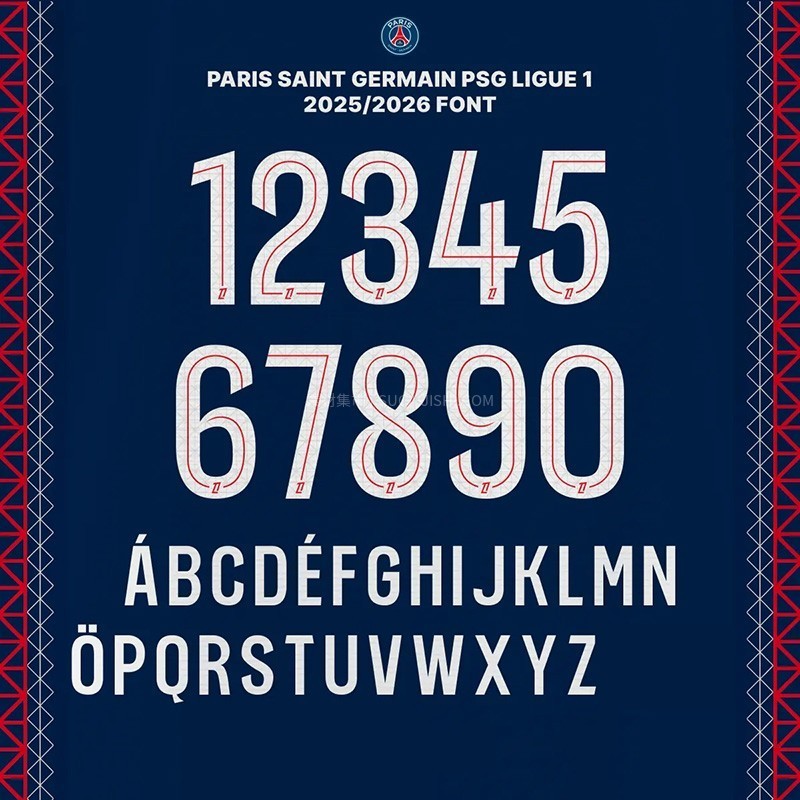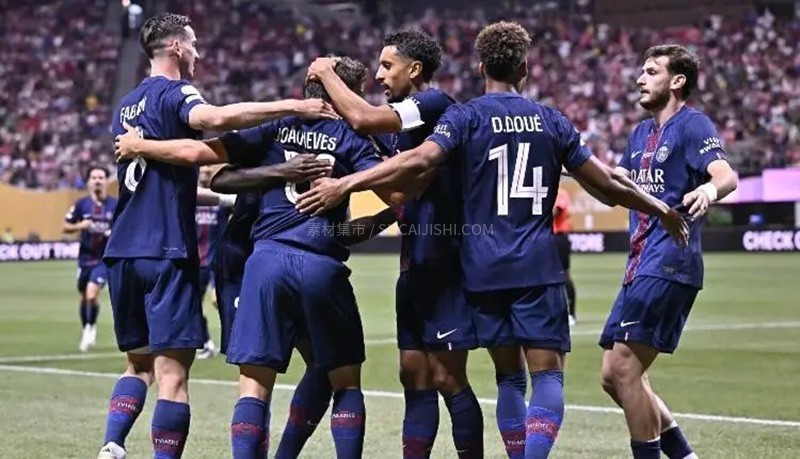
巴黎圣日耳曼为即将到来的法甲联赛 2025-26 赛季的球衣号码和队名字体,灵感源自球队的快速进攻和流畅配合。字体设计以极简主义为核心,线条干净利落,同时在笔画中融入了动态的速度流线,犹如球员在场上风驰电掣的身影。整体风格现代且充满活力,既能确保号码在球场上清晰可辨,又能完美诠释PSG的先锋精神和未来感。